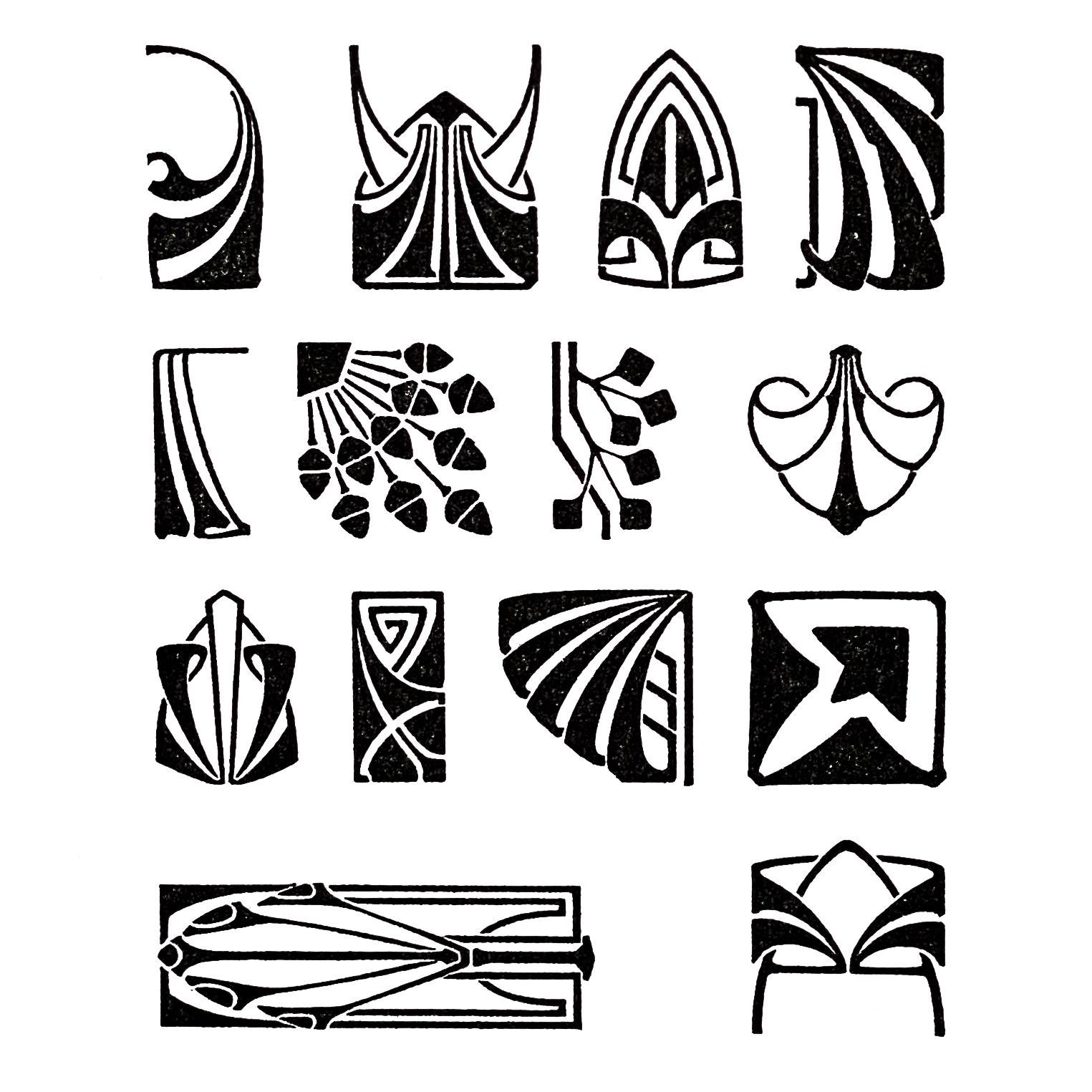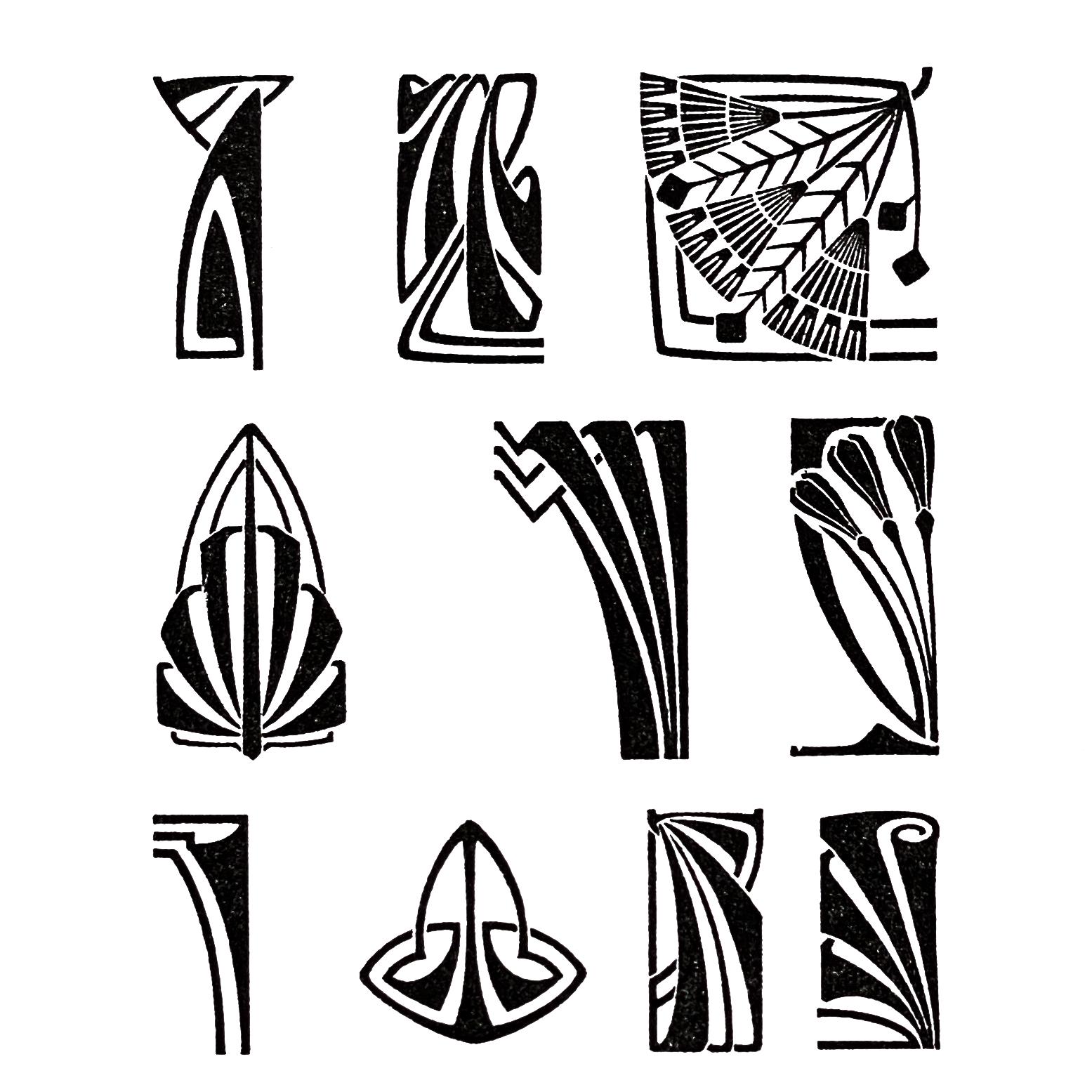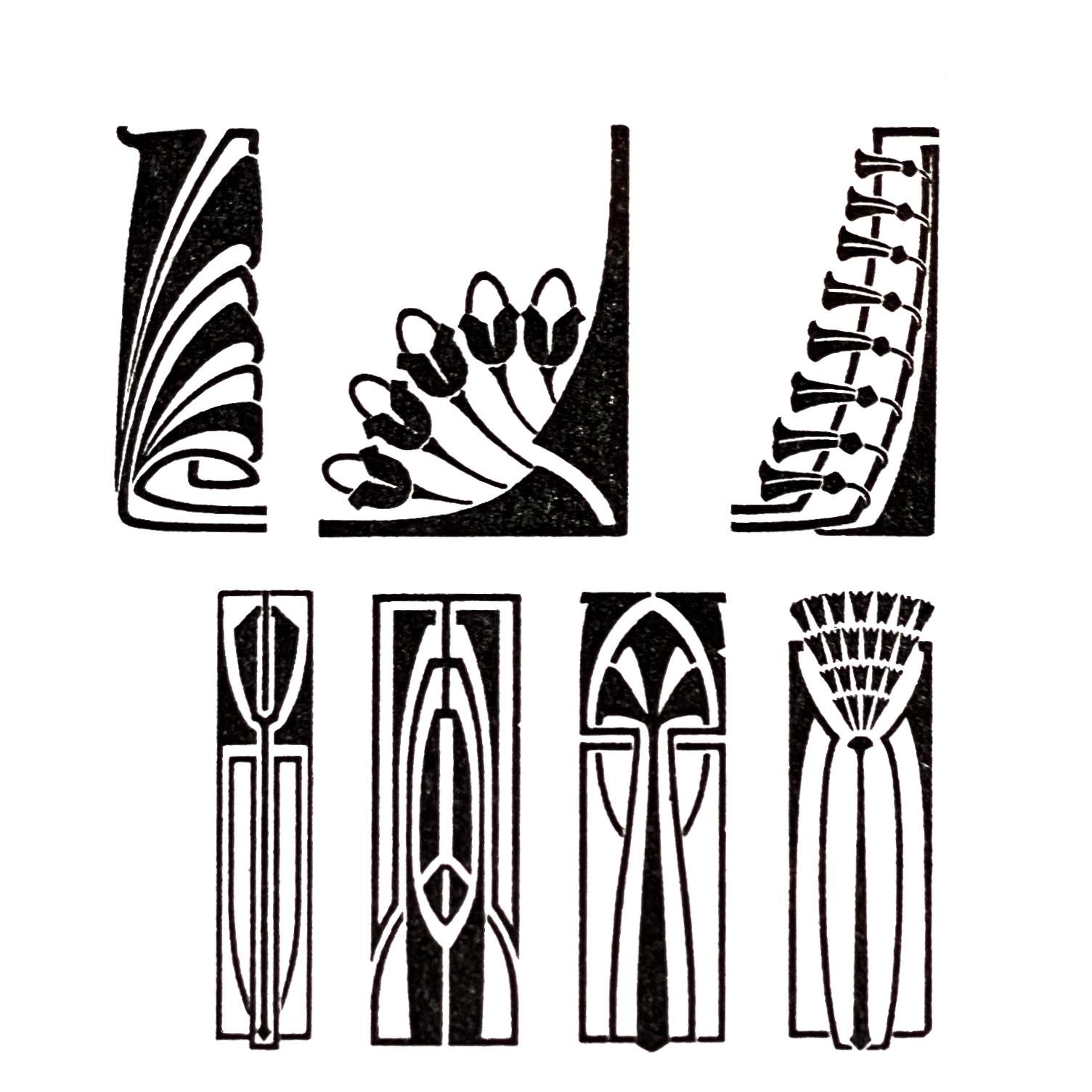
Jugendstil, Bordüren & Zierat
Wie schon angekündigt kommt jetzt noch ein Satz Bordüren und Zierat dazu, ohne den die Jugendstilgestaltung ebensowenig auskommt wie ein Fisch ohne Luft zum Atmen.
Eine Handvoll Ornamente habe ich ja schon nebenher gezeichnet, um meine Schriftproben zu beleben. Jetzt gilt es aber, die Produktion hochzufahren.
Als erstes  mache ich eine Reihe Kombinationsumrandungen und Hintergründe. Das sieht so aus:
Ist es auch im Original so, dass die Kanten rechts und links der Blöcke sichtbar sind? Oder passt du da noch was an? (Even though it’d be a much bigger p.i.t.a.)
Norbert, sieh selbst. Mir persönlich gefällt dieser etwas rustikale Eindruck, denn so erhält sich etwas vom Handgemachten. Aber zum einen paßt das nicht zu den Schriften mit ihren ausgefeilten Kurven, und zum anderen wird es bei Flächenanwendungen noch mehr stören als hier. Ich harmonisiere die Kanten also etwas, wobei ich aufpassen muß, sie nicht zu regelmäßig zu machen, sonst fällt auch das auf.
Übrigens hätte ich hier eine Frage an die Schriftsetzer: welches Punktsystem wurde damals verwendet, um die Höhen und Breiten der einzelnen Teile zu bestimmen? Vermessen dieser Seerosen ergab, daß die Elemente auf dem Faktor 8 aufgebaut sind;  jeweils vier Teile in verschiedenen Kombinationen ergeben die gleiche Länge.
Vermutlich liege ich hier völlig falsch und würde mich über eine Aufklärung freuen.
so finde ich es auch passend; es soll doch etwas für die Adleraugen zu entdecken geben ;-)
Nachdem Norbert mir den Wurm ins Ohr gesetzt hatte konnte ich die Sache nicht gut liegen lassen. So verbrachte ich heute einige Stunden damit, das System dieser Einfassungen zu rekonstruieren. Bestimmt wäre es schneller gegangen, wenn ich in Mathe besser aufgepaßt hätte. Nach etlichen Fehlschlägen fand ich dann aber die richtigen Verhältnisse und konnte so die Linien korrekt angleichen. Der Aufwand wird sich hoffentlich lohnen, denn ich vermute alle diese Umrandungen sind nach demselben System aufgebaut.
Also jetzt nochmal, nahtlos:
Marcus, das wäre dort hilfreich, wo Du etvl. eine Umrandung nur in Stücken verschiedener Grade hast. Wenn alle Elemente einer Verzierung in der gleichen Größe vorliegen, dann macht es für mich keinen Unterschied.
Ich würde gern als Schriftsetzer antworten, aber ich verstehe die Frage nach dem Punktsystem nicht. Es gibt seit langem nur das des Didot-Punkts (in Deutschland). Vielleicht ist etwas anderes gemeint? Höhe und Breite großer Schmuckelemente sind meistens in Cicero abgestuft, also 4 zu 4 Cicero etwa oder 4 zu 2. Man kann sie deshalb zügig in jede größere Form einbauen, weil sie mit dem Blindmaterial übereinstimmen, das auch der Drucker am Schließtisch hat. Die kleineren Versionen sind dann halb und viertel so groß.
Martin,
Punktsystem war der falsche Ausdruck.  "Flächenaufteilung" wäre vielleicht besser. Also nach welchen Regeln wird hier eine Fläche so aufgeteilt, daß sich aus den Einzelteilen eine neue Fläche mit beliebigen Abmessungen nahtlos ausfüllen läßt?
Bei den Seelilien standen die Höhen (ich nehme an das ist der Zeilenabstand minus das Fleisch, denn das sieht man ja im Druck nicht) im Verhältnis 1 : 2 : 3 : 5. D.h. fünf der schmalsten Stücke übereinander sind so hoch wie das höchste Stück. Das Breitenverhältnis ist 4 : 5 : 6 : 7, die nächste Breite ist also jeweils um ein Viertel größer als die vorige.
Meine Frage ist: trifft das nur auf diese Bordüre zu, oder ist das ein Standard? Falls das letztere, dann kann ich mir eine Vorlage machen, die das rekonstruieren diese Bordüren leichter macht, und auch nach Belieben meine eigenen, größeren Teile zeichnen.
Ich hoffe, meine Laienhaften Ausführungen sind verständlich 🙂
Oliver
Nachtrag: ich habe Deinen Kommentar noch einmal durchgelesen, und sehe, was ich oben umständlich beschreibe, auf den Punkt gebracht. So ganz erfasse ich die Sache dennoch nicht. Gibts da Bilder, oder eine schematische Darstellung?
Ich kann den Standard beschreiben, den ich Anfang der 1980er Jahre als etabliert vorgefunden und später in allen Druckereien wiedergefunden habe. Schmuck und Ornamente, die für Flächen und Rahmen verwendet werden, sind systematisch gegossen. Das bedeutet auf Kegeln ab 4 Punkt Stärke und 6 Punkt Länge. Grundlage der Systematik ist das Duodezimalsystem von Punkt und Cicero. Jedes Element soll zügig und ohne Einsatz des Winkelhakens verbaut werden können.